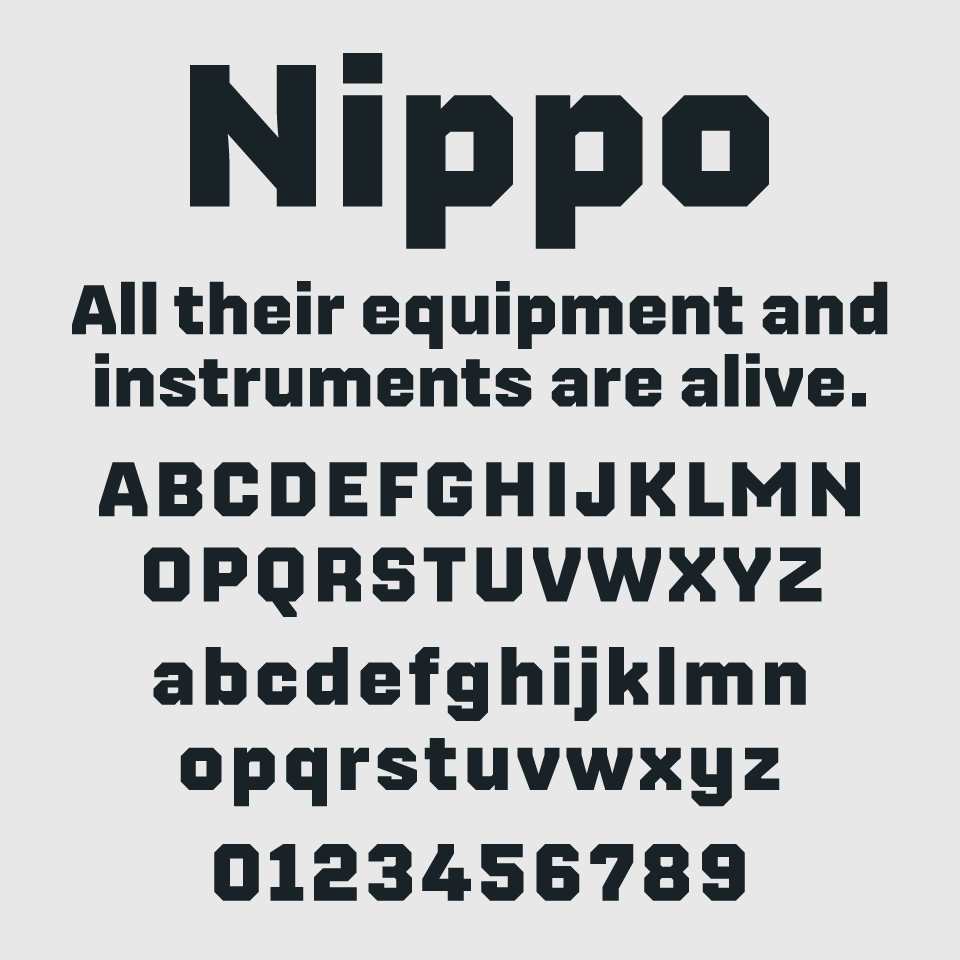
Nippoフォントは、大胆な角張りとどっしりとした存在感が印象的なジオメトリック系のサンセリフフォントです。
直線的で力強い骨格ながら、角にやや丸みを帯びた処理が施されており、無骨さの中にもフレンドリーさを感じさせる設計となっています。スポーツのユニフォームに使われいてような角張ったデザインです。
工業製品や建築物のような安定感があり、ロゴタイプや見出しなど、視線をしっかり惹きつけたい場面に向いています。スポーツ系以外にも、デジタル感やテクノロジー、ゲーム系の世界観とも相性が良く、シンプルながら個性をしっかり主張できるフォントです。